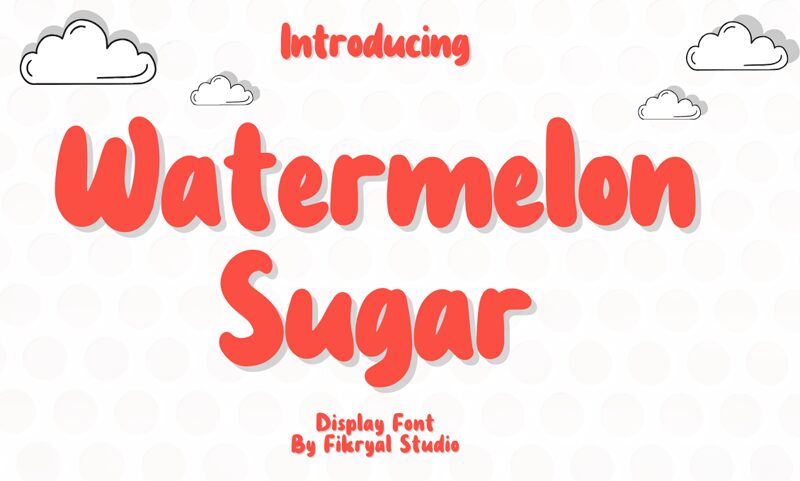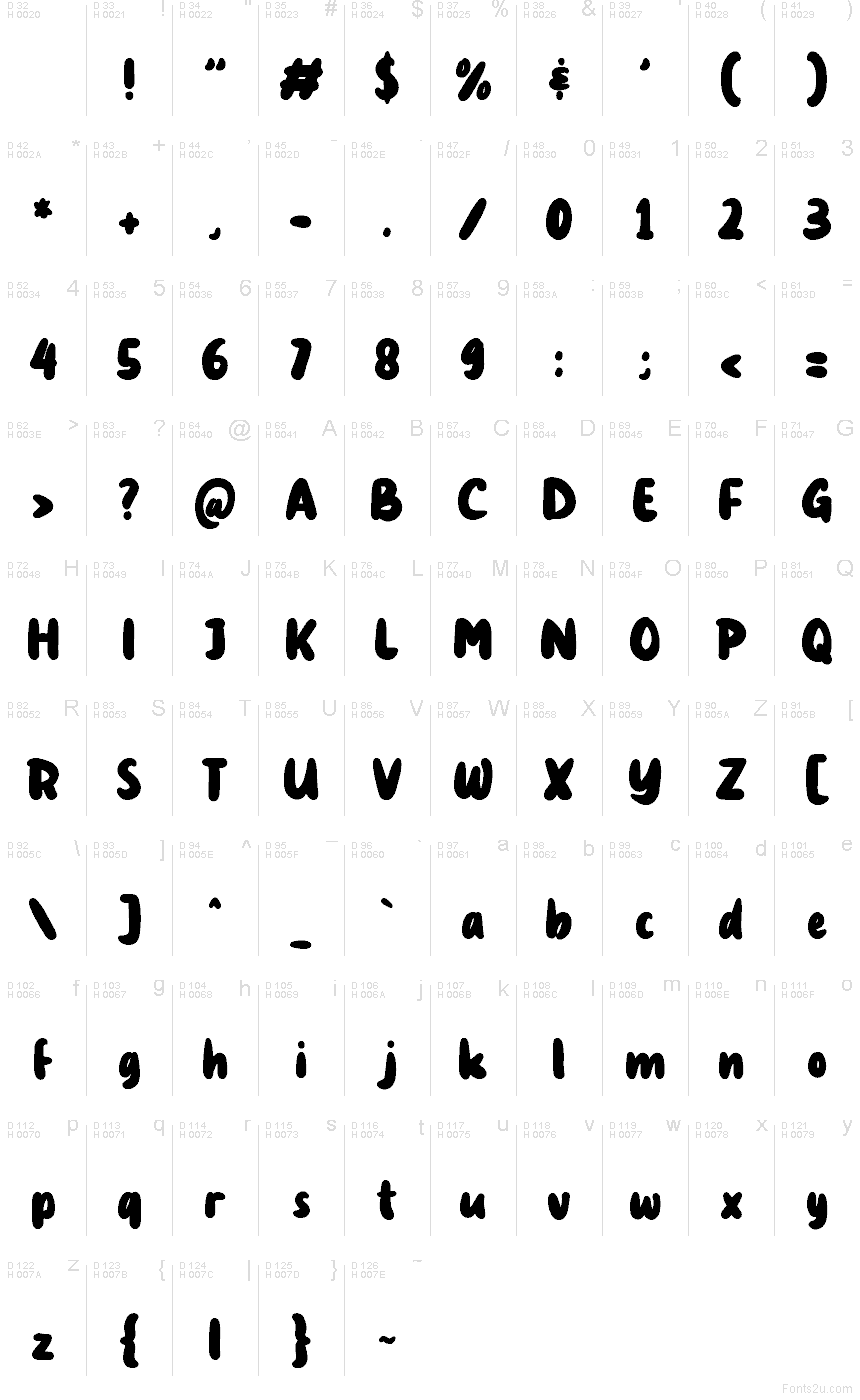
Watermelon Sugar von Watermelon Sugar und Fikryal Studio ist eine kostenlose, abgerundete Pinsel-Script-Schrift mit einer weichen, flüssigen Anmutung. Die Buchstaben fügen sich zu dicken, kompakten Strichen zusammen, deren organische Verbindungen und geschwollene Kurven dem Font eine verspielte und nahbare Ausstrahlung verleihen.
Sie eignet sich hervorragend für Verpackungen von Süßwaren, Café-Branding, Plakatüberschriften, Social-Media-Grafiken und fröhliche Headlines, bei denen ein kurzes Wort einen freundlichen Akzent braucht. Da es sich um eine kostenlose Schriftart handelt, ist sie zudem ideal für Titelkarten, Sticker und Logodesigns, da ihre kräftigen Pinselformen selbst kurzen Wörtern Lebendigkeit und Charakter verleihen.